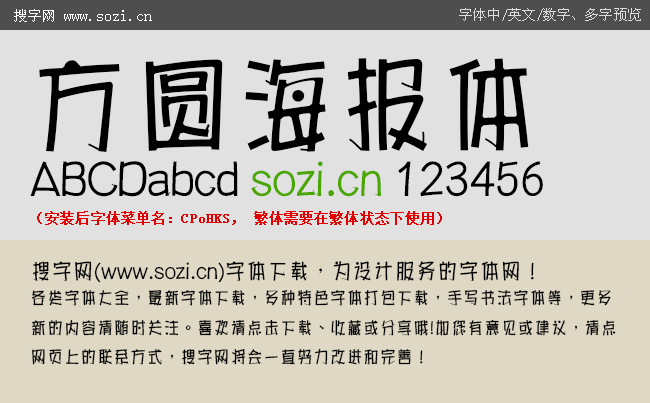
方圓海報體
搜字網(wǎng)提供一款POP風(fēng)格的方圓海報體字體下載,方圓海報體是一款應(yīng)用于設(shè)計方面的藝術(shù)字體,帶有手繪POP風(fēng)格、美觀實用,適用于包裝印刷、廣告設(shè)計、平面設(shè)計、海報設(shè)計等領(lǐng)域。
• 風(fēng)格類別: 海報POP體